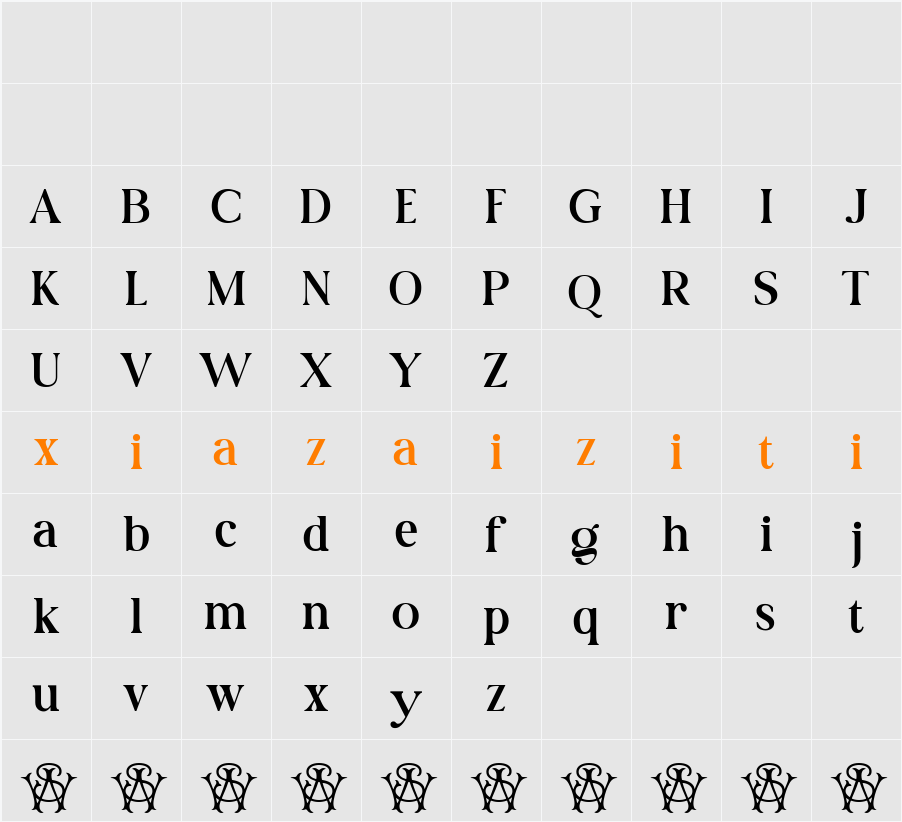
Ws Paradose
Ws Paradose,这款字体结构工整、笔画清晰,兼顾美观与易读性,适用于标题、正文、海报、包装、LOGO 等多种场景。字形优雅稳定,风格百搭耐看,适配日常排版与创意设计,让文字呈现更舒适、更具质感。Ws Paradose一笔一画,皆是细节,以均衡的比例、流畅的线条打造舒适视觉体验,字形端正大气,风格简约现代。无论是商业设计、品牌宣传还是日常排版,都能轻松驾驭,让文字更有格调与力量。Ws Paradose字体下载。